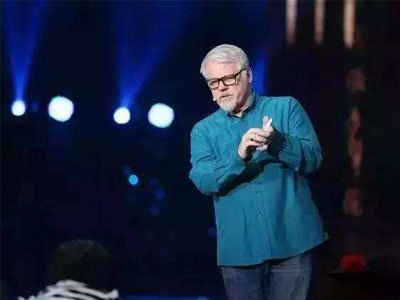
汉字叔叔,一个为汉字痴迷并为之付出一生的美国老爷爷
一位出生在美国小城里的大叔,放着收入优渥的硅谷工程师不做,用毕生精力研究博大精深的中国汉字。几十年的时间,他花光了积蓄,和老婆离了婚、丢了好几回工作,还差点儿被“驱逐出境”,甚至去阎王殿报过到……就仗着这一股子痴狂劲儿,他做到了一件几乎不能完成的事儿。
想知道是啥?跟你聊聊这位“汉字叔叔”的故事吧。
照片中憨厚可爱的大叔名叫理查德•西尔斯,1950年出生在美国西部俄勒冈州的一个小城。当时,那个地方见不到一个黄种人,没有人会说中国话。
抱着橄榄球的小西尔斯和家人在一起
西尔斯渐渐长大,如果不是突然冒出来的“想要去中国学汉语”的想法,他的生活可能和周围的人没有两样。
那会儿中美还没建交。在他爸妈眼里,中国是个封闭、神秘、可怕的地方。“你是疯子、神经病!你去了,命还会有?”
西尔斯选择了“逃跑”。1972年,他靠打工攒够了钱,买了一张单程机票,飞往中国台湾。在台湾,他一边教英语赚钱,一边学习中文。他还取了个中文名字:斯睿德。
汉语并不好学。笔画之间看似没有任何逻辑关联的汉字让斯睿德吃尽了苦头。他渐渐发现:可以通过理解字的原始意义和原始形状来理解汉字的演变。可他并没有找到相应的英文学习资料。
这时,他萌发将汉字字源存入计算机的想法。
直到1994年,这个想法才真正变成现实。那一年,他遭受了突如其来的重病。
一天,他正和朋友聊天吃槟榔,突如其来的心脏病让他晕倒在地。医生告诉他:生命只剩下一年时间。
不得已,他返回美国做了手术,原本健壮地可以跑马拉松的身体突然变得奄奄一息,他开始思索:什么才是最重要的?
“如果生命只剩下一天,我要打电话跟朋友们说再见;如果还剩四十年,那很多重要的事情都可以拖延;如果还能活一年,365天,我决定要电脑化《说文解字》。”
网站开始建起来了,斯睿德自己编程设计。一年过去了,他仍然活着。他雇了一个华裔妇女帮他扫描《说文解字》、《金文编》、《甲骨文编》和《六书通》上所有的字源,这一干,就是7年。
日积月累下来,他扫描的古汉字容量已近天文,几乎涵盖了近百年来成书的全部金石典籍,而这一切,都出自田纳西诺克斯维尔的这间十平米的廉租房里↓↓
2001年,调试基本完成之后,他把网站上线公开,要给全世界看。网页长这样↓↓
当时,网页每天大约有15000个浏览量,大部分是汉语研究者或是中文学习者。斯睿德在网站上开通了捐赠功能,但是一年下来,网站几乎得不到任何捐款。
而网站快建成时,斯睿德在硅谷的高薪工作就没了。他去田纳西做了河道管理员。工作之余,继续做网站。57岁时,他失业了。
古汉语电脑化工程是个资金的无底洞。很快,他20年间攒下的30万美金全部花光,随着他的汉字字源网越办越久,他的生活也越来越清贫。
睡觉打地铺:
随随便便就能对付一顿饭:
这样的日子整整持续了十年。2011年的一天晚上,他忽然发现自己的网站1小时内获得了超过100美元的捐款。这其中发生了什么?
原来,他的网站被一位中国网友发现,转发到了微博上。微博这样说:
“这个人叫Richard Sears。他用20年功夫,手工将甲骨文、金文、小篆等字形数字化处理,上传网络供所有人免费使用。这就是外国人(我猜是美国)的‘傻’吧,这种国家工程,怎么能自己一个人弄呢?您一外国人操的什么心?”
1天之内,他的网站点击量达到60万次,1周内,捐款达到了3万元人民币。这篇博文被不断转发,不少网友跟帖、留言:
“作为一个外国人,却能如此醉心于中国的文字,我还是被震撼了!”
“当年学字体设计时,老师推荐的,真的好用,真心强大。”
“他让我们感动,也该让我们羞愧!”
斯睿德在田纳西的生活从此不再平静。不断有中国记者打来越洋电话采访他。而他也获赠另一个称呼:“汉字叔叔”。
62岁的斯睿德觉得该去中国了。他又买了一张单程机票,飞往中国天津,并定居下来。他的生活依旧清贫:
这是他在天津的小屋,外墙被小广告包围:
冰箱里空空荡荡:
最常吃的是快餐馆的便宜拌面:
待了还不到一年,“汉字叔叔”却几乎要被赶走。他办的是旅游签证,三个月必须离境。一筹莫展之际,他在微博上发了一条求助信息:
这条微博很快便引起网友的关注,并纷纷为他出谋划策。短短十天之内,相关微博便接近15万条。网友们呼吁:“留住汉字叔叔”。
随着媒体报道,汉字叔叔的故事被越来越多的人知道,很多单位也向他发来了工作面试邀请。
最终,北京师范大学接收了他,还给他配了一间办公室和一套两室一厅的专家公寓。斯睿德用英语教物理,一周两节课,每月能拿到4200元工资。
汉字叔叔说: “我很满意,我喜欢这里。我可以安心研究汉字,继续做我的网站。”
闲暇时间,汉字叔叔常常参加各种活动与人分享他的汉字知识。
跟小朋友们讲汉字:
参加电视台节目:
一次,“汉字叔叔”向记者讲起了“侨”字背后的故事。他说:“侨字左边是人,古时写成“n”,象征着一种流浪的人,右边的乔字是这个字的读音,同时也是搬家,迁移的意思。几千年来这个字的意义没有变化,侨就是远离故乡的人。”
2015年“汉字叔叔”和另外两位外国友人一起,入选中华之光——传播中华文化年度人物。组委会给他们的颁奖辞这样说:
他们三个人,六十、七十、八十,他们来自的国度,美国、日本、俄罗斯,都是安享生活的年龄,但他们都不愿贪图安乐,他们来自不同的国家,却又熟悉同一种语言,白发苍苍却活力四射,用不同的工作表达,他们都热爱中国,大洋和雪山隔不断,他们是虹桥,是纽带,是人类文明的使者。
如今,60多岁的斯睿德已然从“汉字叔叔”变成了“汉字爷爷”。年龄在变,但是对汉字的热爱不变。一位外国老人对汉字的一片痴心,令我们感动之余,也让我们深思。